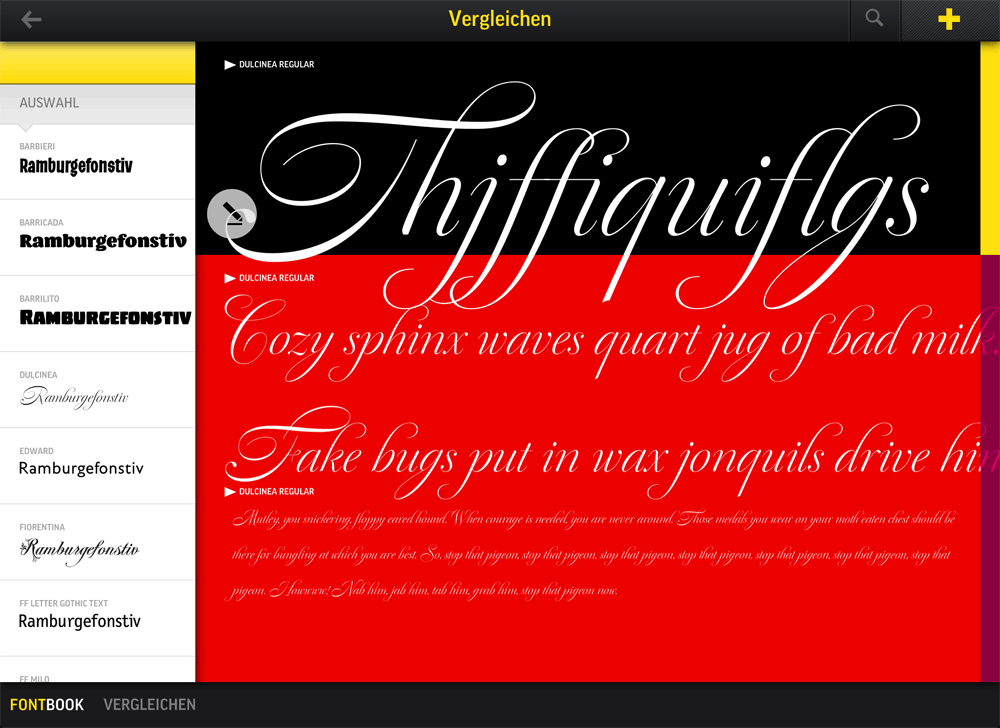
Der neue Script-Font Dulcinea von Ramiro Espinoza ist das Ergebnis einer langjährigen Auseinandersetzung mit der spanischen Barock-Kalligraphie in all ihren Extremen. Die Schreibkünstler Pedro Díaz Morante und Juan Claudio Aznar de Polanco dominierten diese Epoche und beendeten mit ihrem unbändigen, floralen Stil die lange Tradition der disziplinierten, winkeligen Renaissance-Cancellaresca.
Morante war es, der die Schwellzugfeder in Spanien einführten und populär machte. Obwohl sein weltberühmter Text »Arte Nueva de escribir« (Die neue Art zu schreiben), erstmals veröffentlicht 1616, jede Menge Alphabete enthält, die viele Gemeinsamkeiten mit der Breitfeder-Cancellaresca aufwiesen, deutete sich der neue Stil bereits an, so wie ihn Gianfrancesco Cresci in Italien bereits praktizierte.
Die Schwünge der Schriften waren üppig und kompliziert, wobei sie jedoch eine Fülle von Ungereimtheiten aufwiesen. »Ganz knapp an der Hässlichkeit vorbei …« schreibt Ramiro Espinoza in seinen Erläuterungen zur digitalisierten Dulcinea. Und trotzdem enthielten diese Texte eine künstlerische Essenz, die durchaus in Beziehung gesetzt werden kann zum ironischen und manchmal düsteren Charakter des spanischen Barock. »Daher ihr Name – eine Hommage an ›Dulcinea del Toboso‹, der fiktiven Figur in Miguel de Cervantes Roman Don Quijote, die zu seiner imaginären Geliebten wurde.«
Dulcinea im Schriftmusterbaukasten (Compare) der FontBook-App fürs iPad
Und so ist Dulcinea weit mehr als nur ein Revival. Ihre Zeichen sind weder eine exakte Reproduktion der Lettern von Morante und Polanco, noch soll deren Stil digital wiederbelebt werden. »Hätte ich in diese Richtung gearbeitet, wären sehr archaische Buchstabenformen entstanden und eine Schrift, für die es in der heutigen Typografie keine Aufgabe gäbe.« betont Ramiro Espinoza. Trotzdem habe er unzählige interessante Details entdeckt und bewahrt, so dass der spielerischen Geist des Originals enthalten blieb.
Dulcinea bietet raffinierte Optionen für das Setzen von Texten und Überschriften. Zum Beispiel reichlich Ligaturen und Schwungbuchstaben, sowie ausladende Alternativzeichen. Bevorzugte Einsatzgebiete: Mode- und Frauenzeitschriften, Packaging, Rezeptbücher, sowie im Wäsche- und Kosmetik-Marketing.